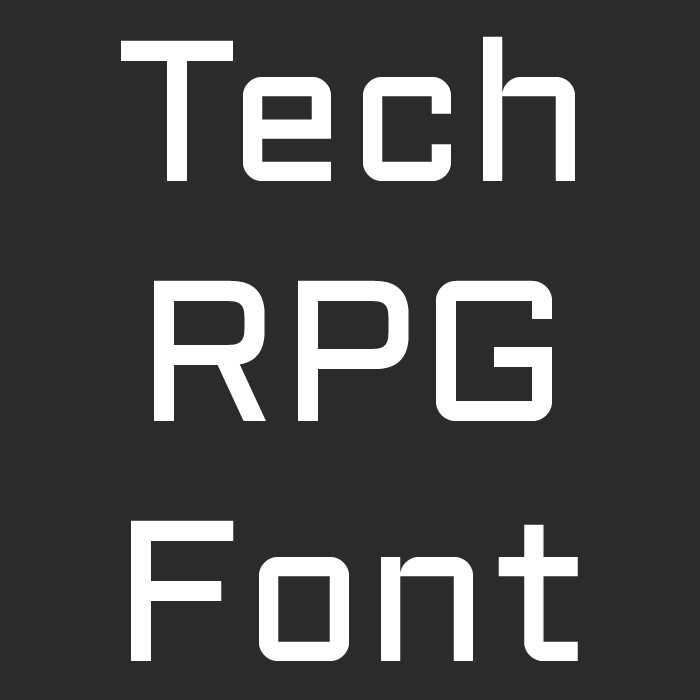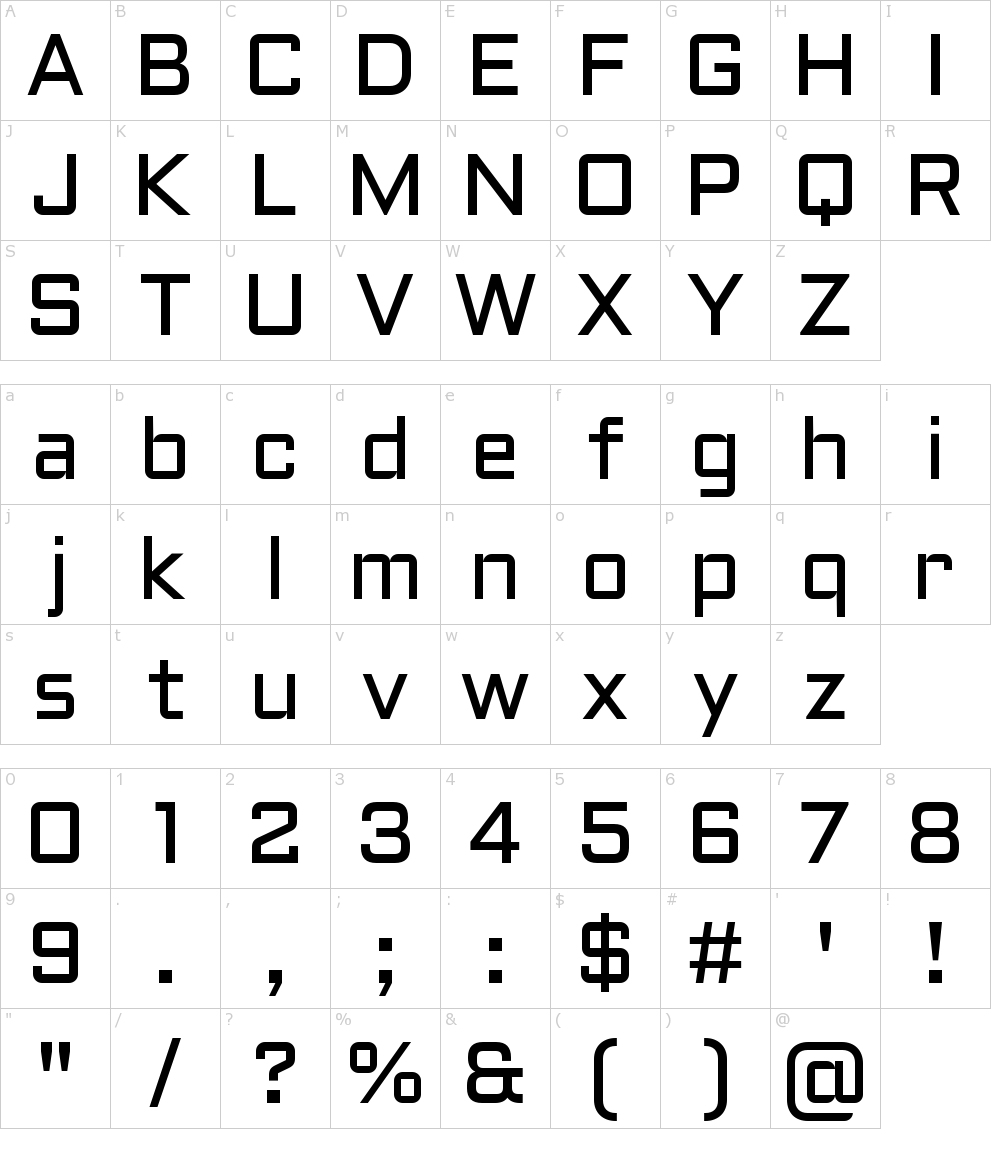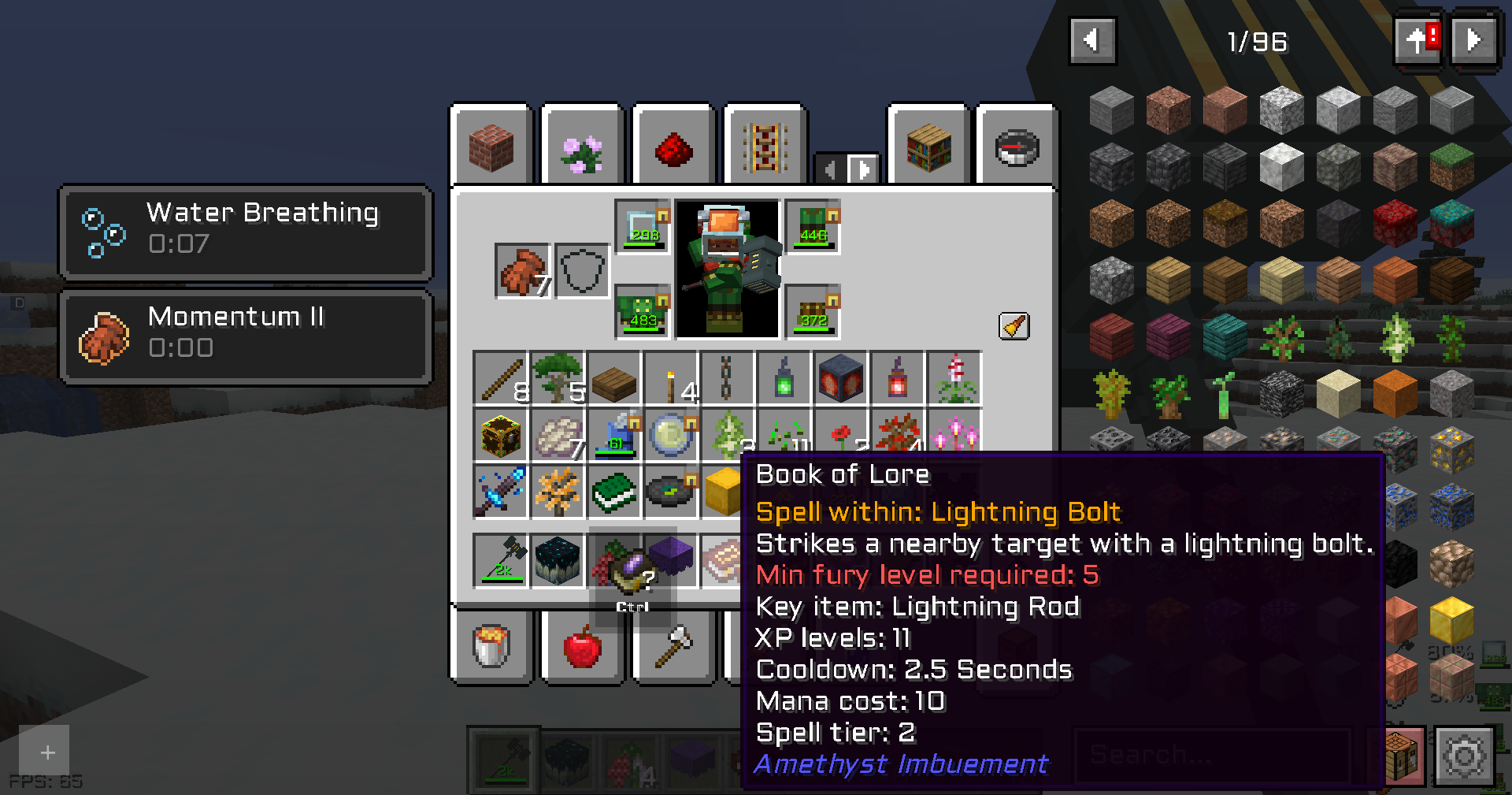
Tech RPG Font для Minecraft: современный шрифт для вашего приключения
Если вы ищете способ освежить интерфейс Minecraft, добавив ему футуристического стиля, Tech RPG Font — отличное решение. Этот шрифт сочетает чёткость, удобочитаемость и технологичный дизайн, идеально подходящий как для модпаков вроде DarkRPG, так и для ванильного геймплея.
🔍 Что такое Tech RPG Font?
Tech RPG Font — это современный шрифт в стиле high-tech, созданный на основе популярного Aldrich от MADType. Он отличается:
- Чёткостью и удобочитаемостью даже в динамичных сценах.
- Футуристичным дизайном, который отлично впишется в техно- и RPG-тематики.
- Поддержкой стандартного и модифицированного интерфейса Minecraft.
Этот шрифт изначально разрабатывался для модпака DarkRPG, но теперь доступен всем игрокам.
🎮 Где использовать Tech RPG Font?
Этот шрифт отлично подходит для:
- RPG-модпаков (например, DarkRPG).
- Технических сборок с модами на автоматизацию (Create, Mekanism).
- Серверов с уникальным стилем интерфейса.
Если вы играете на сервере с друзьями, такой шрифт сделает чат и меню более стильными.
Tech RPG Font — отличный выбор для игроков, которые хотят добавить в Minecraft немного футуристичного стиля без ущерба для удобства. Простая установка, чёткий дизайн и совместимость с большинством версий делают его универсальным решением. Попробуйте — возможно, именно этот шрифт станет финальным штрихом в вашем идеальном Minecraft-опыте!